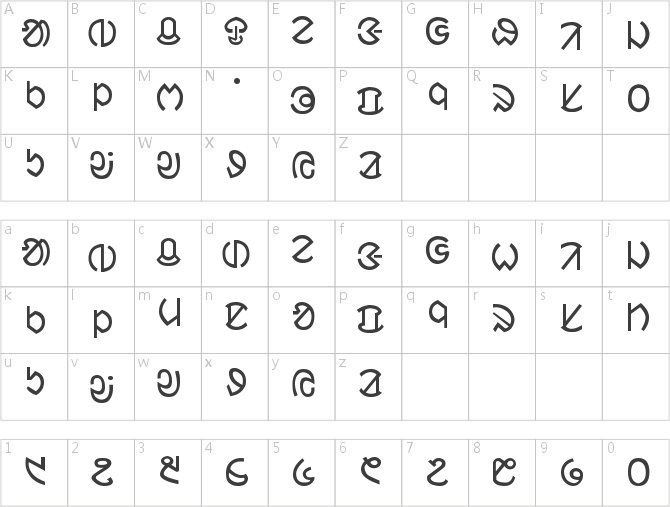
字体名称: ol_ciki
ol_ciki_old(www.santalisong.org
ol_ciki_old(www.santalisong.org字体字库是一款让人赏心悦目、百看不厌的英文字体,适合各类广告和产品包装设计应用,字体大小0.02MB,格式为ttf字体,上传用户是那是不变的,作者/版权方为未知